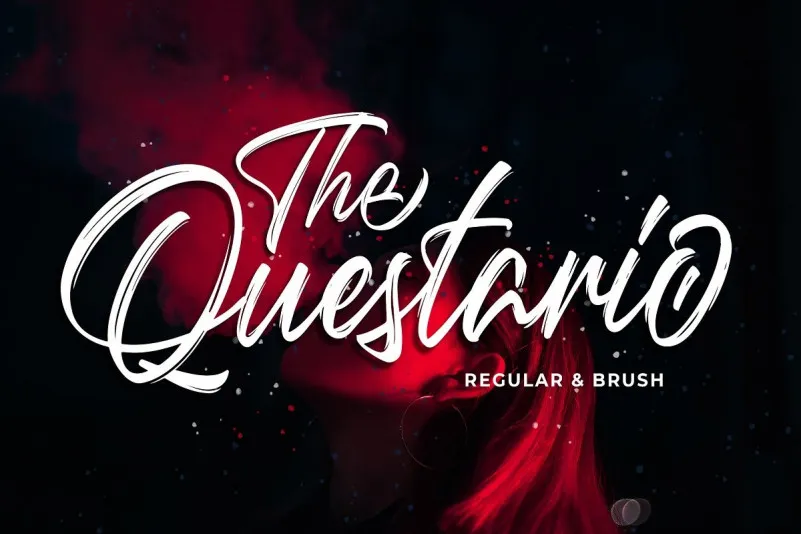
Questario Brush Style Font – Download Grátis
Agrade-se pela sua curiosidade por Questario Font. Este é um novo tipo de letra feito a mão inspirado na calligrafia à laço, oferecendo uma experiência única e forte com texturas de pintura de alta definição. Inspirado nos famosos fontes de escrita à laço, Questario Brush Style se destaca por sua beleza avassaladora e encantadora, mas também mantém um moderno charme. Ideal para aplicativos variados que vão desde cartões de agradecimento até headlines, Questario Brush Style é uma fonte de script versátil. Certificamos que vai adicionar um ar romântico à sua próxima tarefa de arte digital. Nesse espaço convidativo e rico em detalhes, esperamos ser sua escolha perfeita para dar vida aos seus projetos visuais com sofisticação e originalidade.